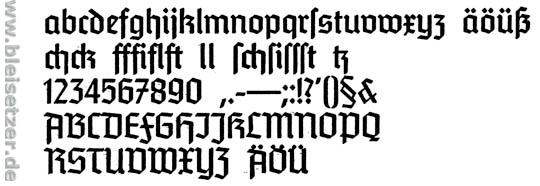
«FAZ» erwägt Abschied von Frakturschrift
Falls man sich für einen Verzicht auf die oftmals als altertümlich empfundene Frakturschrift entscheide, werde eine andere Schrifttype an ihren Platz treten, die die gleiche Funktion erfüllen müsse, nämlich die deutliche Trennung von Meinung und Nachricht.
Ist das überhaupt eine Fraktur? Mir ist so, als ob das eher eine verzierte ist, eine Gotische? Ich hab die FAZ nicht. Aber wo sie nun seit einigen Jahren in Mode und Design wiederbelebt wird, ist sie für die FAZ_Leser "altertümlich", die haben wohle ne Mondfisnternis, die klugen Köpfe?
Die Schriften der FAZ:
Die "Fraktur" ist natürlich, streng genommen, eine Fraktur-Variante der Gruppe Xe. Es gibt viele Kanzlei-Frakturen, die in diesem Stil auftreten.
Die FAZ hat sich schon immer über ihr strenges Layout ohne Bilder auf dem Titel abgetrennt vom typischen Zeitungslayout anderer Verlage. Das ist historisch gewachsen und war lange Zeit sehr erfolgreich. Und bis heute spielt die FAZ meinungsmachend in einer speziellen Liga, an die nur noch sehr weniger Zeitungen in Deutschland herankommen - und keine einzige Tageszeitung; vielleicht mit Abstrichen die Süddeutsche.
Das Problem der FAZ ist seit langem ein ganz anderes.
Der klassische Anzeigenmarkt bricht seit Jahren ein. Das Geld aber verdient ein Blatt wie die FAZ zu einem Großteil nur über die Anzeigen. Es gab und gibt viele Firmen, die als eine Art Product Placement Stellenanzeigen in die FAZ setz(t)en, um sich imagefördernd zu bewerben. Aber die Arbeitswelt hat sich verändert - auch im mittleren und oberen Management.
Und nun sitzt man bei der FAZ wie das Kaninchen vor der Schlange.
Egal, was man macht, es wird die Wellen hochschlagen lassen. Also versucht man es mit der schrittweisen Änderung des Layouts. Das funktioniert aber ab einem gewissen Punkt nicht mehr. Dann muß ein großer Schritt gemacht werden.
Und die FAZ wird diesen Schritt gehen. Und alles wird zur Disposition stehen: Schriften, Bild-/Text-Integration, ja sogar ein neues Format. Da bin ich mir sicher.
PS: Übrigens habe ich (nur am Rande und nicht direkt involviert) in meiner Atex-Zeit ähnliche Statements von Fachleuten bei der FAZ gehört. Aber das ist ja auch gerade 'mal erst ca. 20 Jahre her.
Tolle Idee.
Ich mag sie nicht, diese "Nazischriften". Ich kenne die ganze Geschichte. Aber, es tut mir leid, sie sind verseucht. Ich assoziiere immer "Deutschland, ...!" Gefallen mir nicht.
Anders sehe ich das bei der Überlegung, auch Fotos auf der Titelseite zu drucken. Das mag ich nun gar nicht. Für mich ist jeden Morgen die FAZ ein Augenschmaus (bis auf diese "Nazischriften", siehe oben). Ein Gegenpol zur BILD- und Bilderwelt unserer modernen Medien. Anders formuliert: Eigentlich kuck' ich sowieso schon zuviel Fernsehn ...
Ergänzung: Solange Barbara Klemm die Bilder macht, möchte ich nichts gegen Fotos in der FAZ gesagt haben. Aber nicht auf dem Titel!
Hä...? Wie kann denn eine Schrift "verseucht" sein? Ein Text -- ok, aber eine Schrift? Verstehe ich recht: Du weißt, dass die Fraktur weder historisch noch in irgend einem anderen Zusammenhang (mal davon abgesehen, dass irgendwelche Neonazi-Deppen in Ermagelung besseren Wissens ihren braunen Mist oft in gebrochenen Schriften verfassen) zum Nationalsozialismus steht und es sind dennoch Nazischriften? Die Meinung hat was! Hoffentlich kommt niemand auf die Idee die Erde wieder für eine Scheibe zu halten ...
Ich bemerke in den letzten Jahren sowieso eine redaktionelle Annährung der FAZ an die SZ. Sofern man nun auch noch das m.E. passende Layout ändert, sehe ich (der ich in Süddeutschland lebe) auch keinen einzig weiteren Grund mehr meine Tageszeitung weiterhin in Frankfurt zu ordern.
"Deutschland, Deutschland ... " -- au weiha
Tobber
verstehe ich auch nicht ganz, sharif.
ich würde es verstehen, ginge es dir mehr um die gebrochenen formen,
bzw. wenn du sie nicht mehr zeitgemäß fändest. aber damit 'deutschland,
deutschland ...' zu assoziieren ist genau so ein quatsch wie alle 'glatzenträger'
Nochmal zum Thema Tannenberg:
Zu der kann man wohl mit Fug und Recht sagen, daß sie eine Nazischrift ist: Plump, ohne Formqualität, alles gleichgemacht. Eine Schaftstiefelgrotesk wie man so treffend sagt.
Ah, wiedermal ein Typo-Mythos! :wink:
Das sind die Schriften, die den Rest der gebrochenen Schriften in Verruf gebracht haben, bzw, ihr Einsatz.
Nur der Einsatz und nichts sonst. Die Form ist völlig unpolitisch. Was du als »gleichgemacht« bezeichnest, war eine ganz normale »Modernisierung« des Stils, wie die Entwicklung der Grotesk aus der Serif.